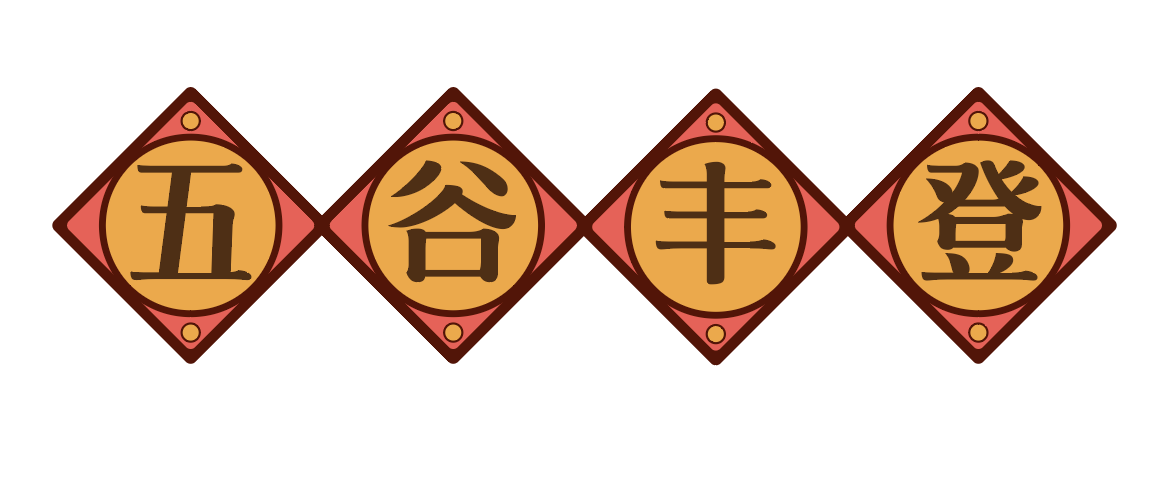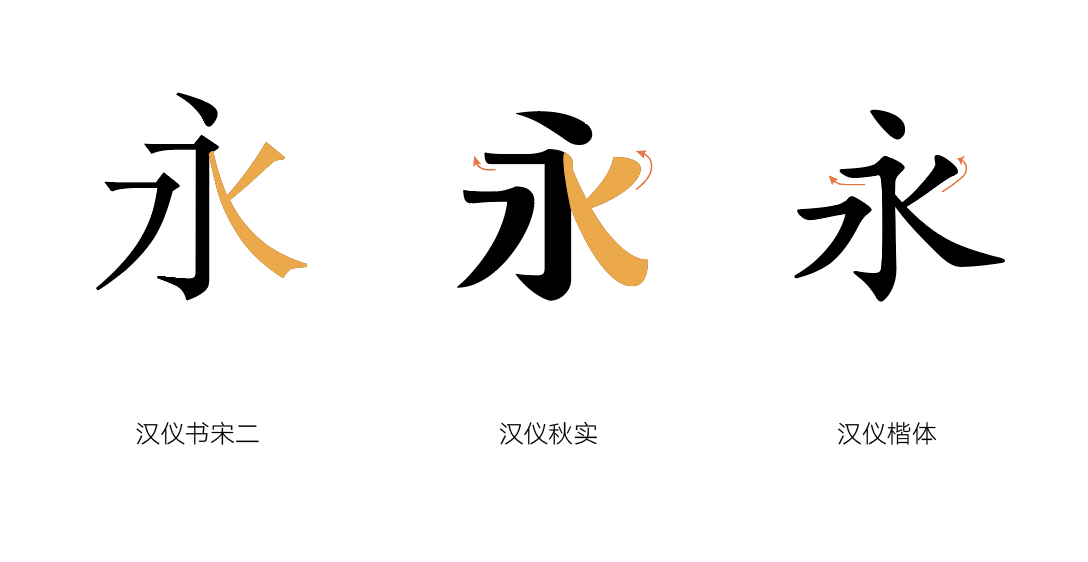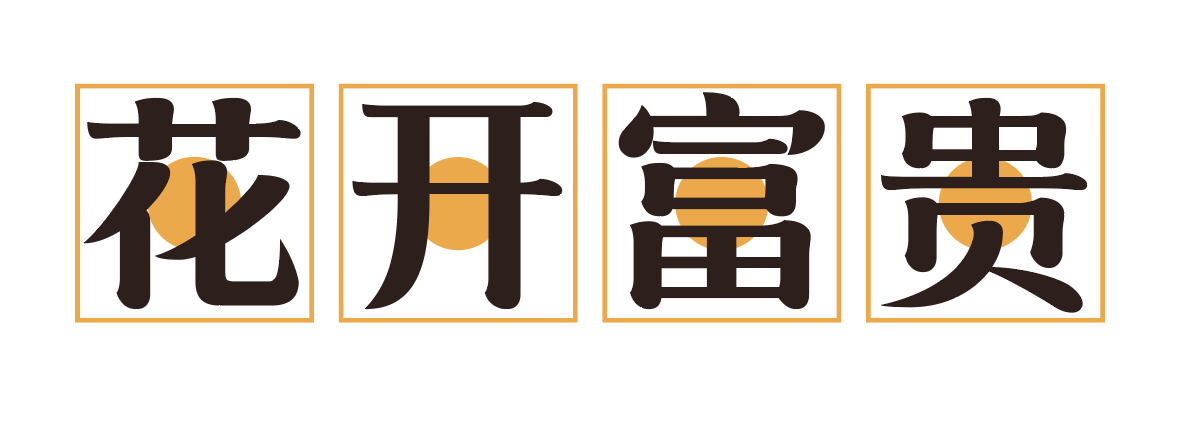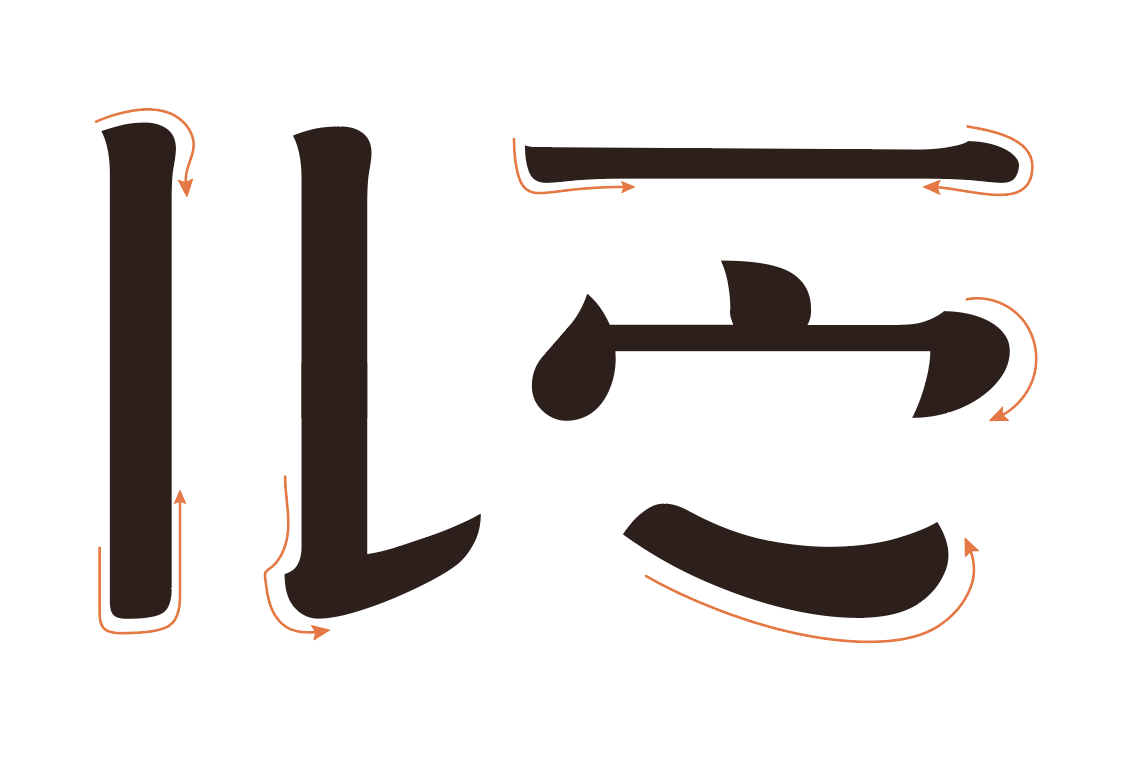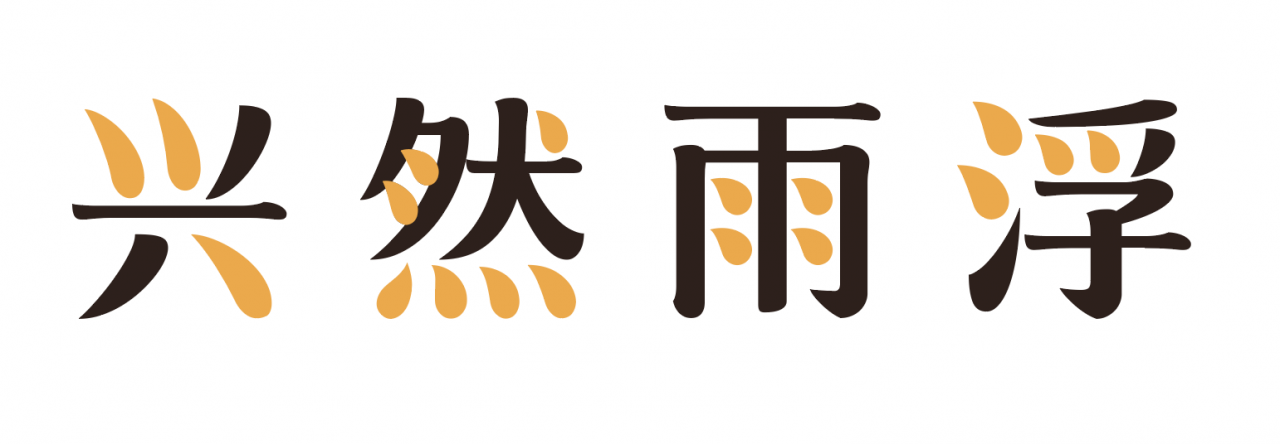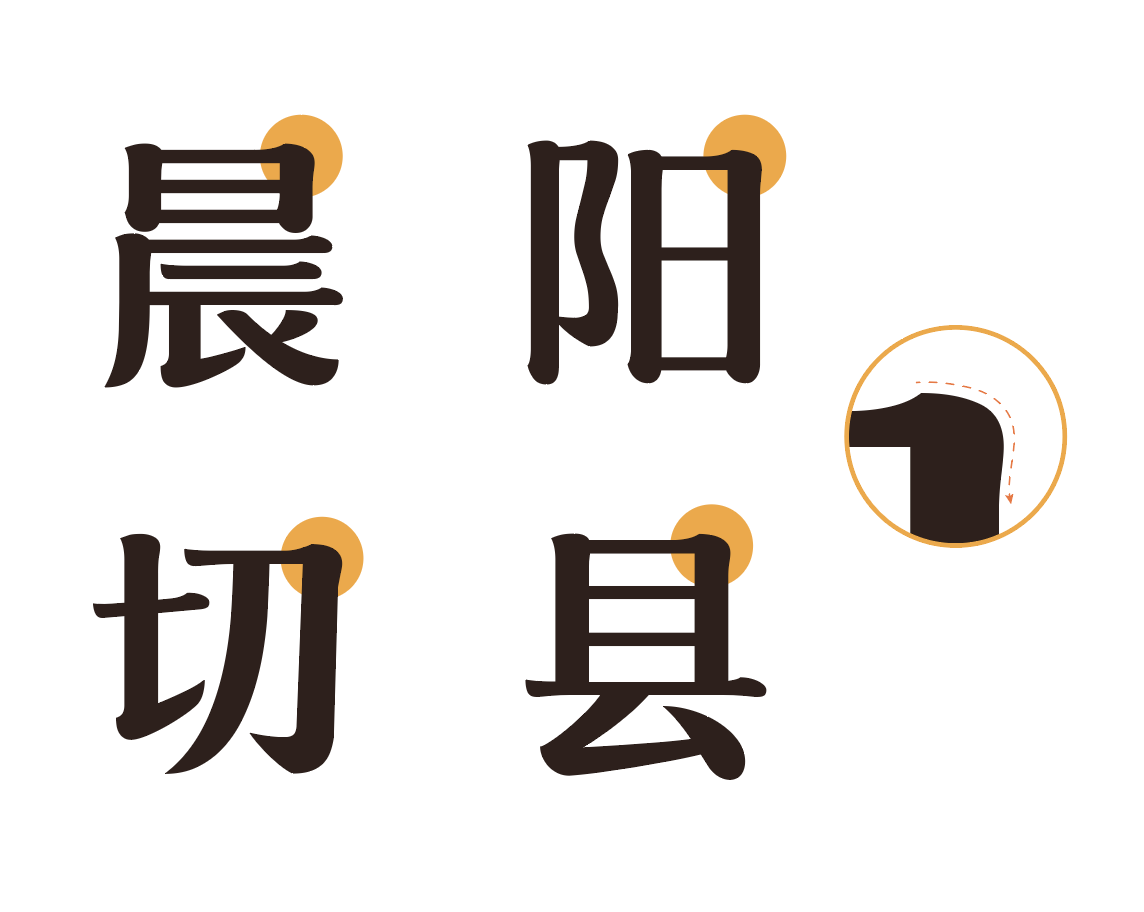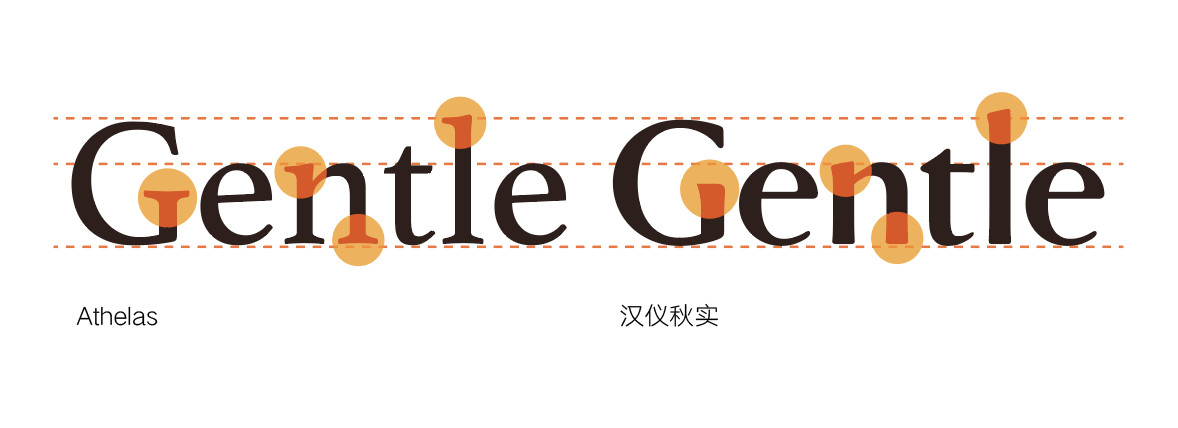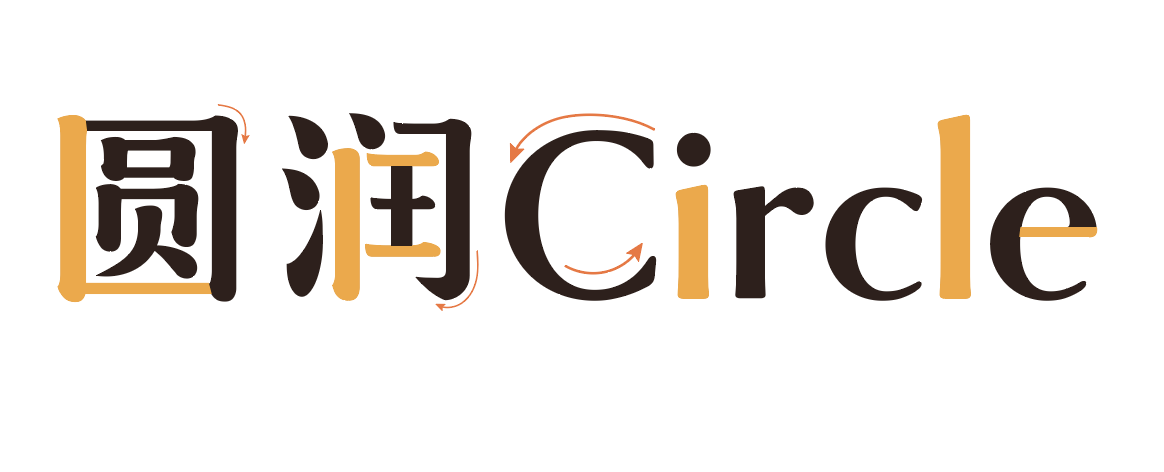
汉仪秋实 W
汉仪秋实 | 整体特点
汉仪秋实是一款创意美术字体。它是在宋体的结构基础上,融入了楷体书法的笔画特征,从而达到了一种圆润、流畅、柔美的设计效果。这款字体端庄文雅,适合在稳重的、温暖的、有情调的设计场景中使用。
汉仪秋实的笔画穿插结构与宋体一致,运笔走势与楷体相似。但是与汉仪书宋二和汉仪楷体相比,汉仪秋实的字形更加饱满,笔画更加丰腴。
汉仪秋实 | 字形结构
汉仪秋实的字形端正,字面大小一致,字体中宫舒展放松,重心平稳,布白均匀,整体和谐统一,作为标题字阅读起来十分舒适。
汉仪秋实 | 笔画特点
汉仪秋实的起笔收笔都保留着书法运笔的痕迹。这款字体的笔画较为粗重,笔势顺畅圆润,线条挺拔有力 。
汉仪秋实的“点”笔画虽然在不同位置上有着不同的展现形式。但是都浑厚圆润,传递出一种厚重朴拙的感觉。
汉仪秋实的笔画转折间有楷书的韵味,折角曲线圆滑富有弹性。
汉仪秋实 | 西文特点
汉仪秋实的西文在衬线体的基础上加入了中文字体的笔画特点,弱化了衬线的特征,曲线更加圆润饱满。
汉仪秋实西文字体粗细笔画的搭配,形成了与中文一致的风格。
汉仪秋实 | 中西文搭配
汉仪秋实西文的设计参考借鉴了中文笔画的书写方式,使中西文搭配更加和谐统一。